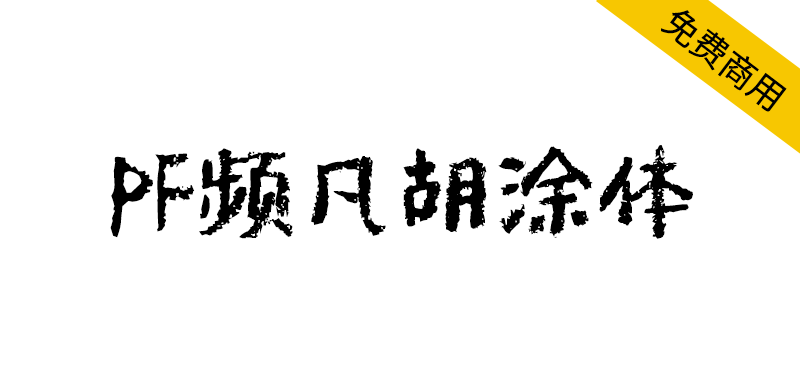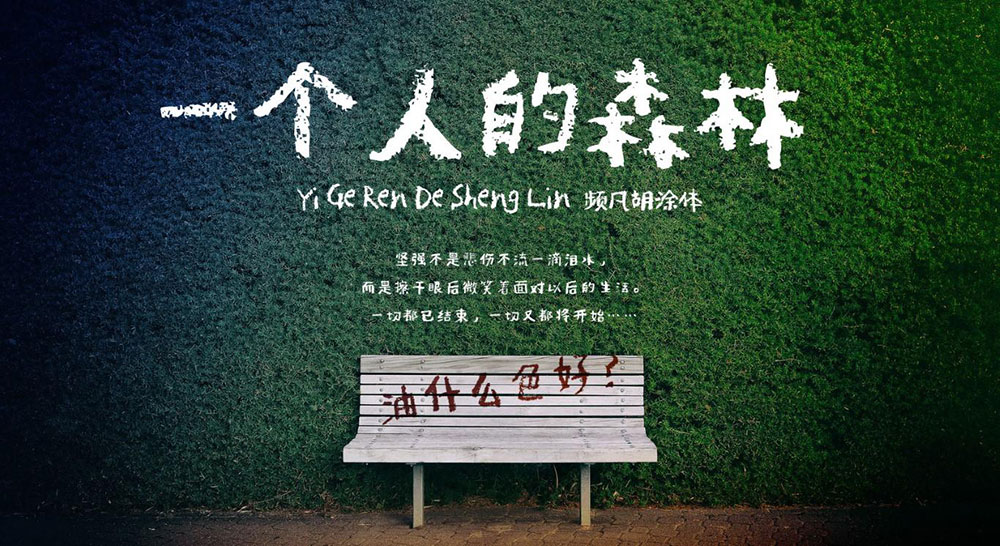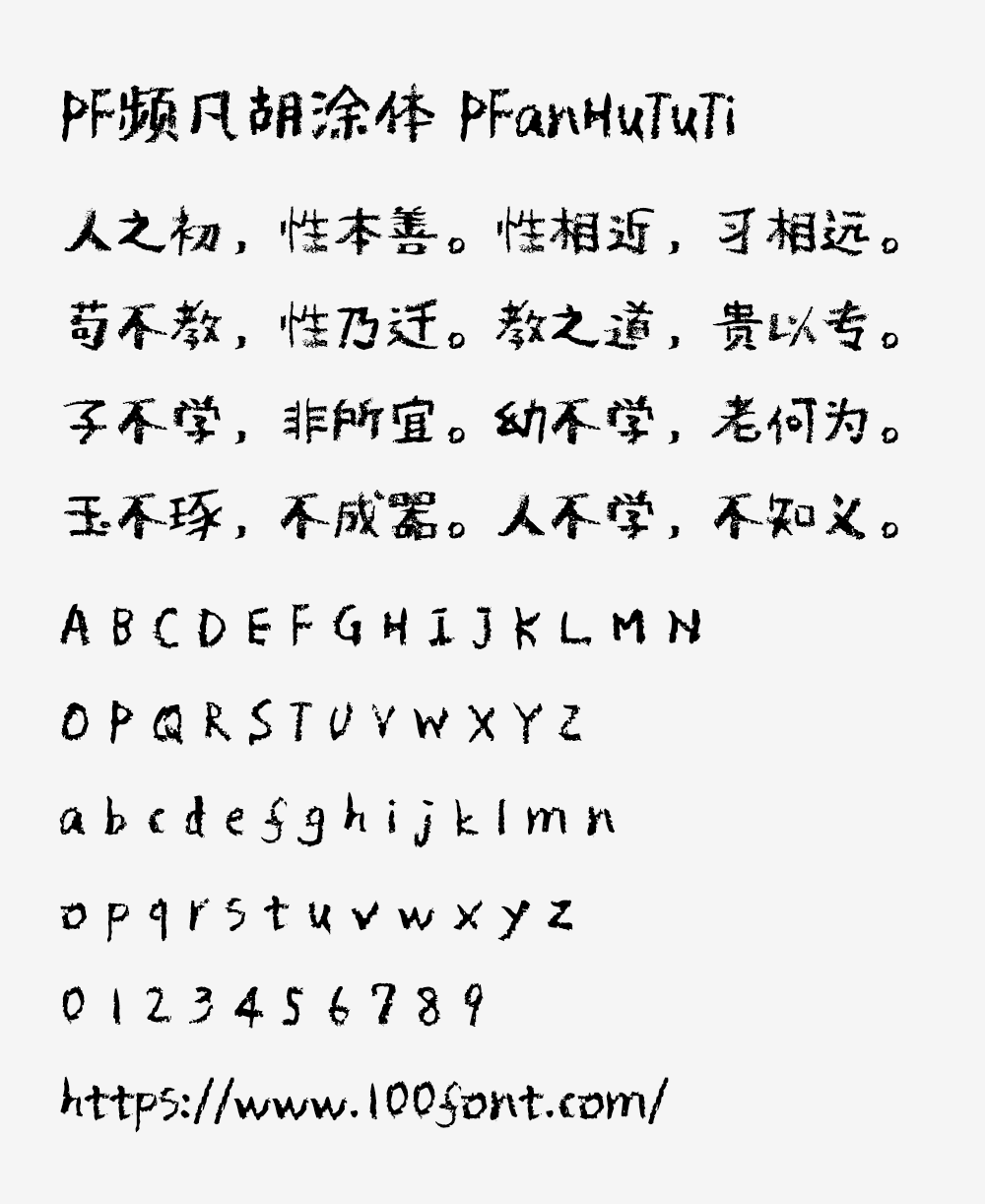
字体来源:给儿子生日制作画面标题时,偶然发现这款日文字体,频凡感觉非常适合。奈何整体完成度较低,只含括二千余汉字,且多为日系繁体字形。字体应用后愈加喜欢,相遇即有缘,权当一份未来的生日礼物,遂产生增补冲动。字体命名来源于自己中年对”难得糊涂“的理解及字体涂鸦的本身。
字体风格:这是一款手写字体,视觉上如同油漆/蜡笔在不平的表面涂抹,留下斑驳厚重的墨迹。粗糙中流露温柔,岁月感不显沧桑,纯手工赋予的文艺气质,推荐应用于动漫标题诗歌短文等场景。
调整字形:原字随性浪漫,字符大小不一,更有“逼真的笔迹感”;但因此使用性非常有限,字符堆叠难予辨认,尤其不适合文本。基于设计感与阅读性的平衡,促进字体完成度,统一了字符宽高,逐字调整字符大小。同时,发现并修改原有日系字形,使其更加贴合简体中文规范和习惯。